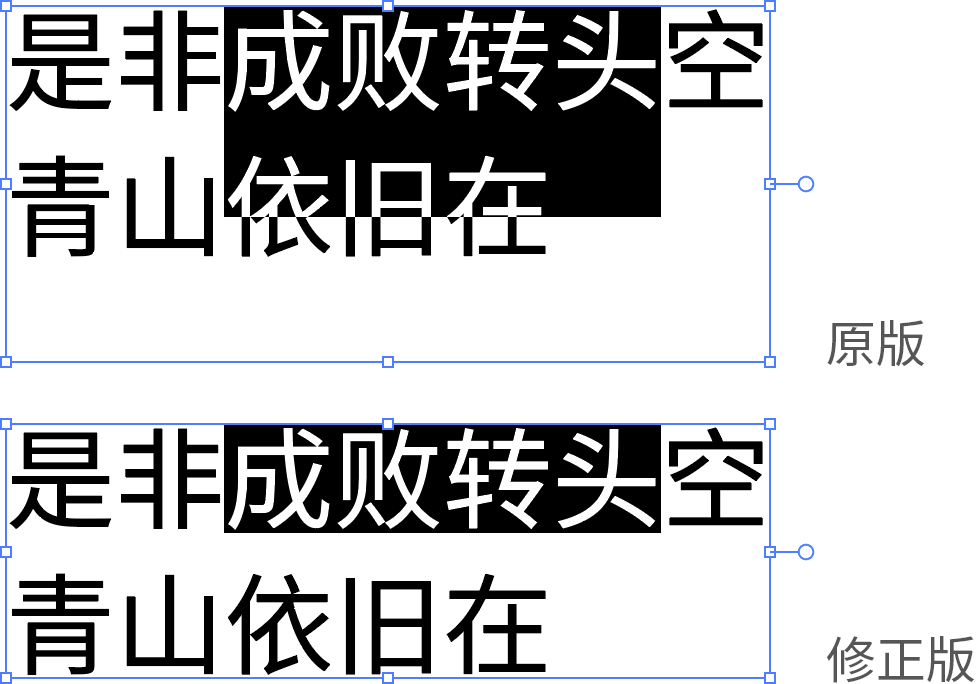
思源宋体 (行高修正版)
介绍
原版思源宋体的定界框比一般字体的大很多,这导致在 Photoshop、Illustrator 等软件中使用时,文本框下方会出现一段多余的空白。甚至当选中文字时,选区(反色区域)会遮盖住下一行的内容。这都对使用造成了一定的困扰。
此修正版基于 Adobe 官方发布的 SC 版修改,SC 版的文字写法遵循中国内地标准,且字数齐备,支持简体中文、繁体中文、日文、韩文等,适合中国内地用户使用。
我们修改了字体中 head 和 CFF 两个表中的定界框数值,没有改动任何其他内容,可放心使用。